หากใครกำลังมองหาฟอนต์สวยๆ สไตล์ตัวเขียนภาษาอังกฤษ เหมาะกับธีมงานสไตล์หวานๆ เช่น การ์ดแต่งงาน เบเกอรี่ หรือร้านดอกไม้ ใช้งานได้หลากหลาย ไปโหลดกันเลยค่ะ
รวม 30 ฟอนต์ (Font) โหลดฟรี สไตล์ลายมือตัวเขียนสวยๆ
ตัวอย่างฟอนต์ฟรีทั้ง 30 แบบ
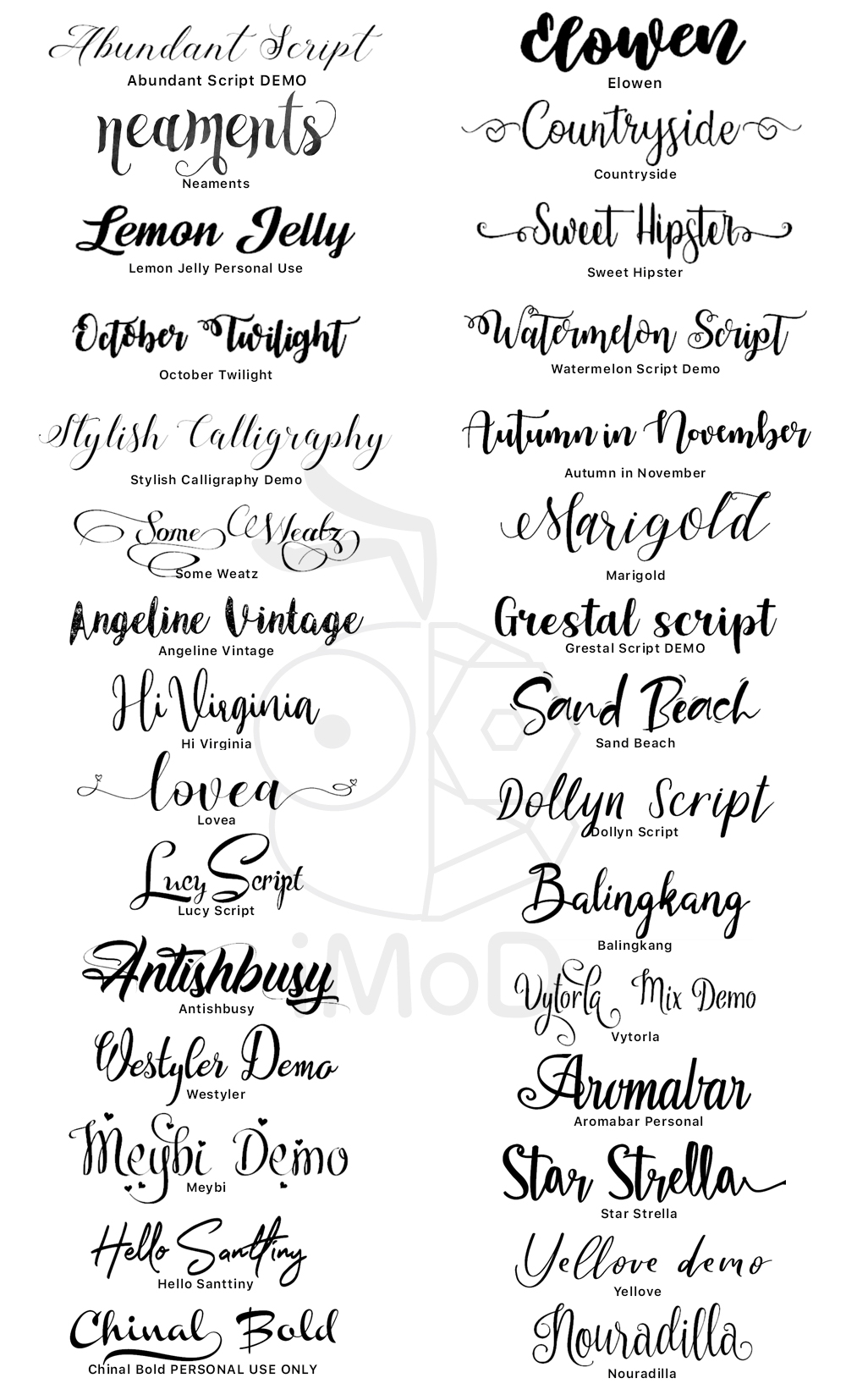
- Neaments
- Abundant Script DEMO
- Elowen
- Countryside
- Lemon Jelly Personal Use
- Sweet Hipster
- October Twilight
- Watermelon Script Demo
- Stylish Calligraphy Demo
- Autumn in November
- Some Weatz Font
- Marigold
- Angeline Vintage
- Grestal Script DEMO
- Hi Virginia
- Sand Beach
- Lovea
- Dollyn Script DEMO
- Lucy Script
- Balingkang
- Antishbusy
- Vytorla
- Westyler
- Aromabar Personal
- Meybi
- Star Strella
- Hello Santtiny
- Yellove DEMO
- Chinal Bold PERSONAL USE ONLY
- Nouradilla